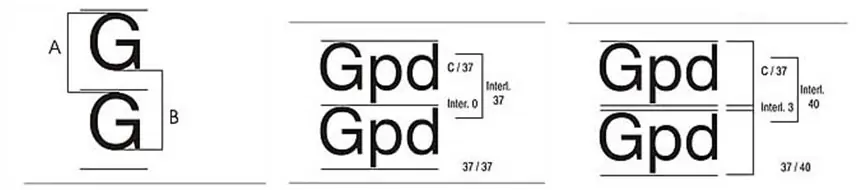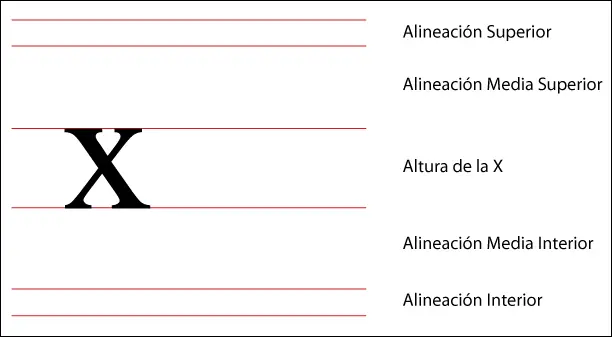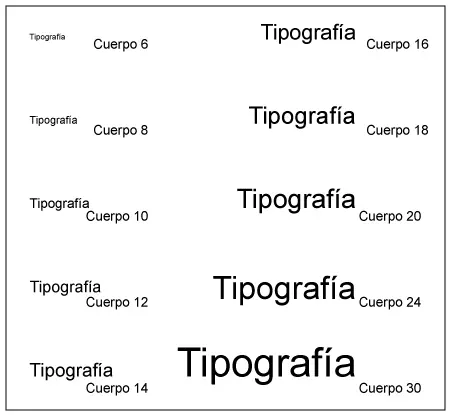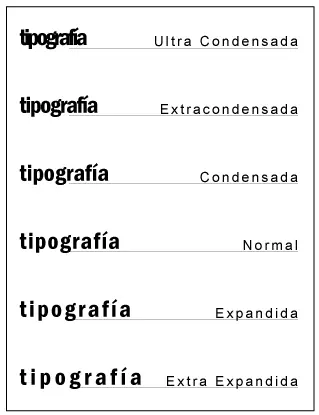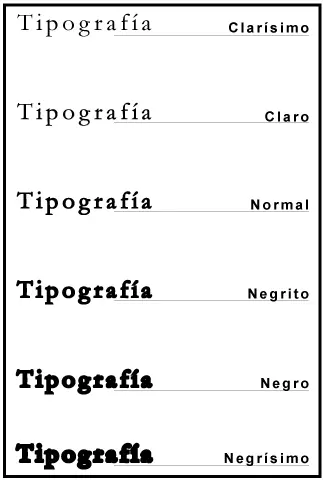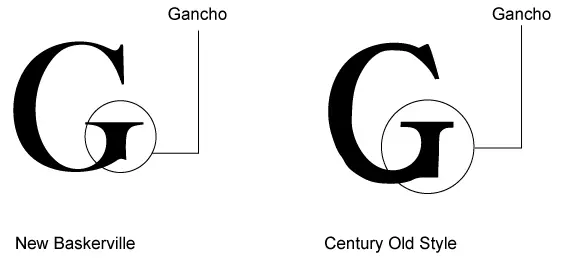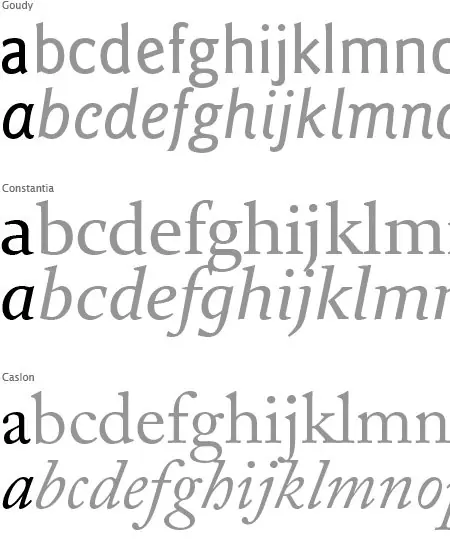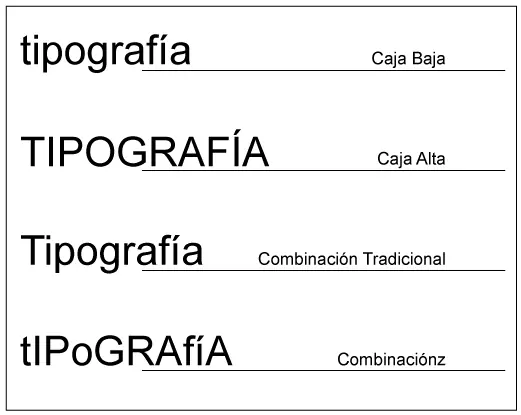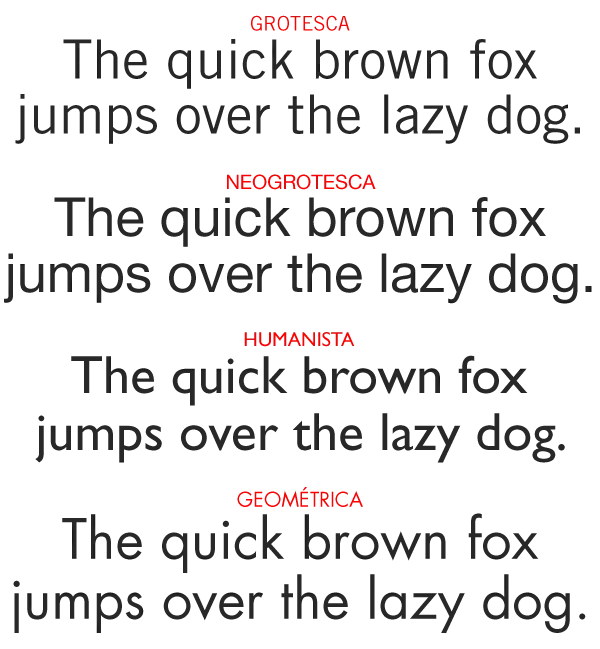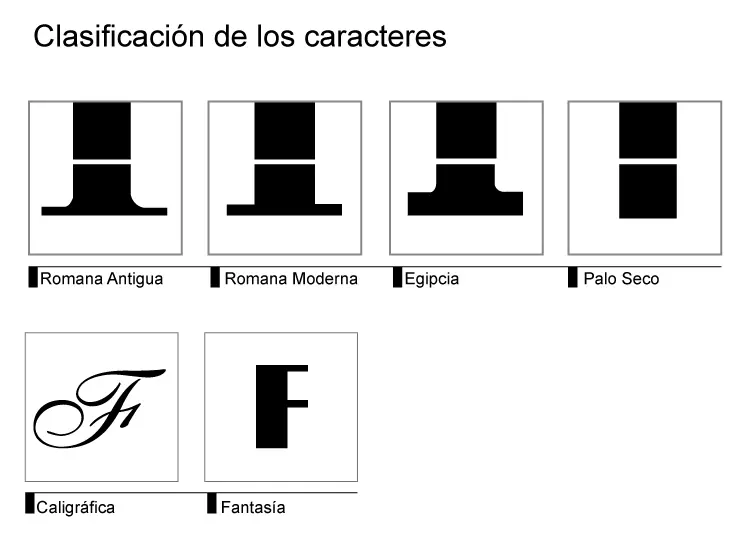
PRINCIPIOS BÁSICOS EN LA TIPOGRAFÍA
El arte de la tipografía consiste en hacer legibles y atractivas visualmente las palabras y los signos gráficos que las acompañan.
Los orígenes de la palabra impresa se remontan a los tipos móviles tallados en madera inventados por Gutenberg en Alemania, los cuales, a lo largo de un rápido desarrollo, evolucionaron hacia la impresión de tipos metálicos. En los sistemas de composición se ha producido una evolución constante hasta desembocar en los actuales sistemas de composición, completamente electrónicos.
Esta evolución ha ido influyendo a lo largo de todo su proceso en la apariencia y en la estructura de la letra, tanto para ganar calidad y legibilidad de su forma como para evolucionar en un sentido puramente estilístico, ya que la aparición de nuevos y más avanzados sistemas de fotocomposición permitió ir matizando los diseños, así como complicando el trazado de la letra, avances estéticos imposibles de conseguir con anterioridad debido a problemas meramente técnicos. Se trata de una evolución que es necesario conocer. (Ambrose Harris. Fundamentos de la Tipografía. Editora Parramont. USA).
En cuanto a la legibilidad, se considera que los textos de largo alcance se leen más fácilmente cuando se presentan en caja baja y en una familia tipográfica de estilo romana antigua como por ejemplo la Garamond. Sin embargo para las palabras o frases cortas de una señalización, las familias tipográficas aconsejadas son las del grupo sin serif o paloseco, de estilo neogrotescas o con modulaciones en el trazo, como por ejemplo la fuente Helvética.
ESTRUCTURA
El vocabulario usado para la descripción de las diferentes partes de una letra, se compone de una serie de términos acuñados desde hace mucho tiempo y que se asemejan a los usados para describir las partes de nuestro cuerpo. Así las letras tienen brazos, piernas, ojos, y otras partes como cola y asta de las que afortunadamente nosotros carecemos (la mayoría).
De todas formas, creemos que debido a las tradiciones del oficio en los diferentes países, no hemos visto todavía que la descripción de las partes de una letra coincida de forma unánime en los libros sobre tipografía y diseño. En todo caso, los términos que aquí se muestran constituyen un buen bagaje para comprender y conocer las distintas partes de una letra, y han sido en cierta medida consensuados a partir de las fuentes consultadas.
ÁPICE
Unión de dos astas en la parte superior de la letra.
APÓFIGE
Pequeño trazo curvo que enlaza el asta vertical con los terminales o remates.
ASTA
Rasgo principal de la letra que define su forma esencial. Sin ella, la letra no existiría.
ASTA ASCENDENTE
Asta de la letra que sobresale por encima de la altura de la X (ojo medio).
ASTA DESCENDENTE
Asta de la letra que queda por debajo de la línea de base.
ASTA ONDULADA O ESPINA
Rasgo principal de la S o la s.
PERFIL, FILETE O BARRA
Línea horizontal entre verticales, diagonales o curvas.
BRAZO
Trazo horizontal o diagonal que surge de un asta vertical.
BUCLE O PANZA
Trazo curvo que encierra una contraforma.
COLA
Prolongación inferior de algunos rasgos.
CONTRAFORMA O CONTRAPUNZÓN
Espacio interno de una letra total o parcialmente encerrado.
CRUZ O TRAVESAÑO
Trazo horizontal que cruza por algún punto del asta principal.
CUELLO
Trazo que une la cabeza con la cola de la g.
ESPOLÓN
Extensión que articula la unión de un trazo curvo con otro recto.
GOTA, LÁGRIMA O BOTÓN
Final de un trazo que no termina en una gracia o remate, sino con una forma redondeada.
HOMBRO O ARCO
Trazo curvo que sale del asta principal de algunas letras sin acabar cerrándose.
LAZO
Trazo que une la curva con el asta principal.
OJAL
Bucle creado en el descendente de la g de caja baja.
OREJA
Pequeño trazo situado en la cabeza de la g de caja baja.
PATA
Trazo diagonal que sirve de apoyo a algunas letras. También se puede llamar cola.
SERIF, REMATE O GRACIA
Trazo terminal de un asta, brazo o cola. Es un resalte ornamental que no es indispensable para la definición del carácter, habiendo alfabetos que carecen de ellos (sans serif).
UÑA O GANCHO
Final de un trazo que no termina en remate, sino con una pequeña proyección de un trazo.
VÉRTICE
Punto exterior de encuentro entre dos trazos en la parte inferior de la letra.
LÍNEAS DE REFERENCIA DE UNA LETRA:
En los tipos, la posición de las letras no responde a criterios arbitrarios. Todas ellas han de compartir unas zonas comunes que quedan definidas por cuatro líneas limítrofes que nos enmarcan cada una de las letras y contribuyen a realzar su trazado.
La línea principal es la llamada línea de base, y sirve de apoyo a las letras en su trazado. Sirve de base y asiento, siendo la referencia principal de la que nos servimos para ubicar las letras formando palabras dentro de un texto. Es, además, la línea compartida a partir de la cual trazamos las restantes de referencia en el trazado de una letra.